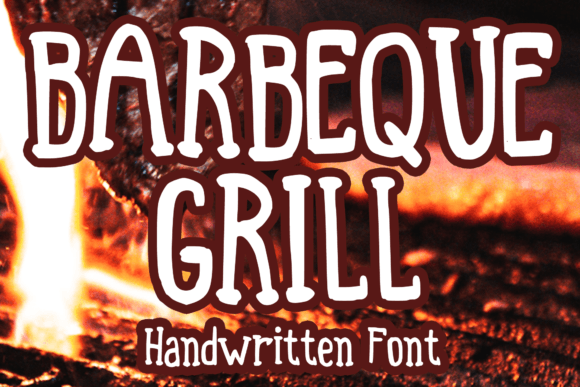
Barbeque Grill
Barbeque Grill – A Fonte Skinny que Transforma Qualquer Projeto
Se você está em busca de uma fonte que combine leveza, diversão e estilo casual, a Barbeque Grill chega como a escolha perfeita. Criada com traços finos e um toque “bouncy”, ela traz aquele clima descontraído que faz qualquer design respirar boa energia.
Por que escolher Barbeque Grill?
- Versatilidade total: Ideal para camisetas, capas de livros, menus de restaurantes, cartões de felicitações, adesivos e pôsteres.
- Leveza visual: Seus traços finos evitam poluição visual, permitindo que o conteúdo seja o protagonista.
- Toque divertido: O estilo “bouncy” adiciona movimento e personalidade sem precisar de imagens adicionais.
Onde a Barbeque Grill brilha?
Com base em testes reais de designers, a fonte se destaca em situações onde a vibe casual é essencial:
- Moda e camisetas: Cria slogans que chamam atenção nas estampas.
- Menus de cafés e restaurantes: Dá um ar acolhedor e moderno ao cardápio.
- Convites e cartões: Transmite simpatia e personalidade em festas e eventos.
- Stickers e merchandise: Aumenta o apelo visual de produtos promocionais.
- Posters e flyers: Garante legibilidade mesmo em formatos grandes.
Barbeque Grill não é apenas mais uma tipografia – é um estilo de vida para quem quer imprimir boa vibração em cada detalhe visual. Experimente hoje mesmo e descubra como essa fonte skinny pode transformar seus projetos, tornando‑os mais leves, divertidos e memoráveis.